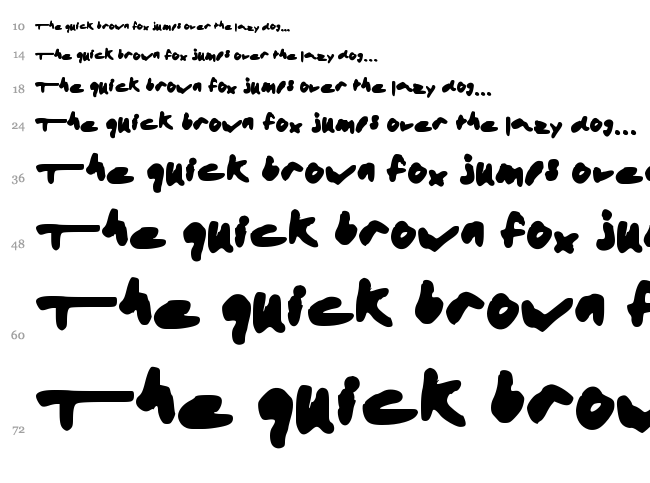
Шрифт Marker SD , Рукописные — Рукописные шрифты
Русские рукописные шрифтыПри составлении и написании любого текста необходимо уделять внимание его оформлению, а именно шрифтам. Не забывайте о том, что главная цель любого текста — донести до аудитории вашу идею, однако внешний вид также помогает и способствует этому.
Хочу привести вам 15 примеров рукописных шрифтов, которые обрели достаточно широкое распространение, скачать их сегодня можно совершенно бесплатно. Обычно они используются при создании приглашений, грамот и придают любому тексту особую элегантность и изысканность.
Как известно, хорошего много не бывает. Это касается и шрифтов. Красивый сбалансированный шрифт может стать украшением любого проекта. Но поиск подходящего начертания порой может занять очень много времени, особенно, если дизайнеру нужен рукописный шрифт. Такие шрифты отличаются от серифов и сан-серифов тем, что зачастую имитируют почерк дизайнера или его видение того, как должен выглядеть рукописный шрифт. Нельзя сказать, что таких шрифтов мало, напротив, их явный переизбыток.
Рукописный шрифт King Basil, созданный дизайнером Мисси Мейер, отличается плотными штрихами, но при этом он очень мягкий и немного женственный. Шрифт бесплатный, его можно задействовать в самых разных проектах, как цифровых, так и печатных. King Basil отлично подходит для создания логотипов, им можно набирать заголовки, делать анонсы различных мероприятий.
Создательница Milkshake Лаура Уортнигтон стремилась сделать универсальный, дружественный и удобный для чтения рукописный шрифт. И ей это удалось на 100%. Шрифт получился очень удачным, в меру массивным, но не грубым. Символы гармонично перетекают, все буквы хорошо сочетаются друг с другом. Milkshake получился немного винтажным, глядя на него, почему-то вспоминается логотип Coca-Cola.
Шрифт Variane разработал арт-директор агентства Work Ins Studio Вой Моч Томи. Этот потрясающий рукописный шрифт напоминается о старом добром классическом дизайне и даже удивительно, насколько удачным он получился – ведь для создателя это дебют. Шрифт плотный, символы несколько вытянуты по вертикали, но смотрится очень легко. Отлично подойдет для заголовков, логотипов, его можно использовать в самых разных проектах, ведь он выглядит очень элегантно.